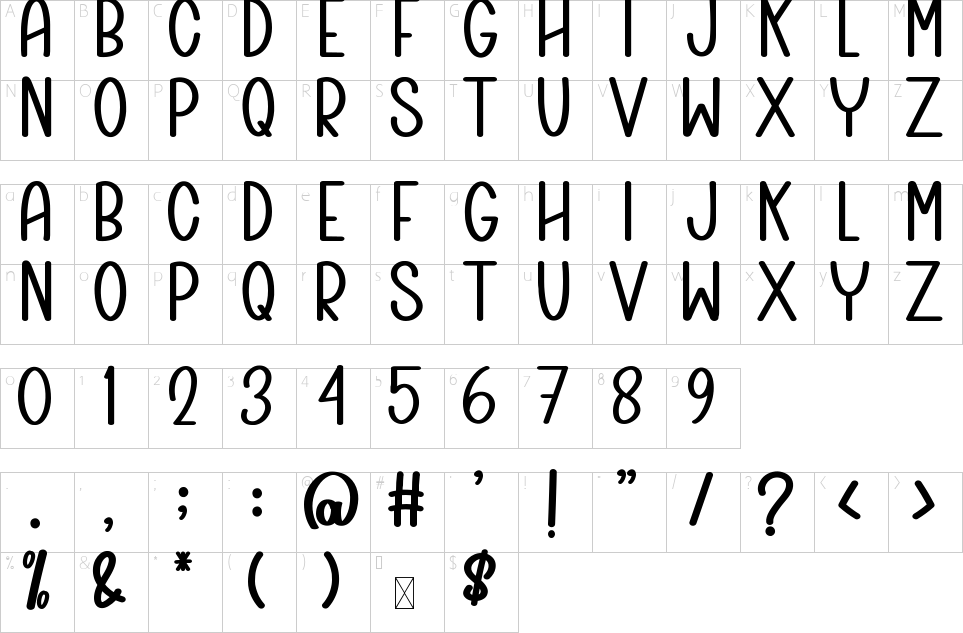
Descubra a diversão no Design com Drawing Sandwich Font. Esta elegante e criativa fonte foi desenvolvida pela InermediaSTUDIO, uma equipe dedicada que busca inspirar os designers digitais por meio de sua arte digital única. Com seus traços fluidos e detalhes únicos, esta font pode transformar simples textos em trabalhos de arte incríveis. Adquira Drawing Sandwich para Windows e Mac hoje. Mais de 350 designers já descobriram o prazer nessa fonte criativa, e agora é sua vez de se juntar a eles. Instale-a e deixe seu design ganhar vida.